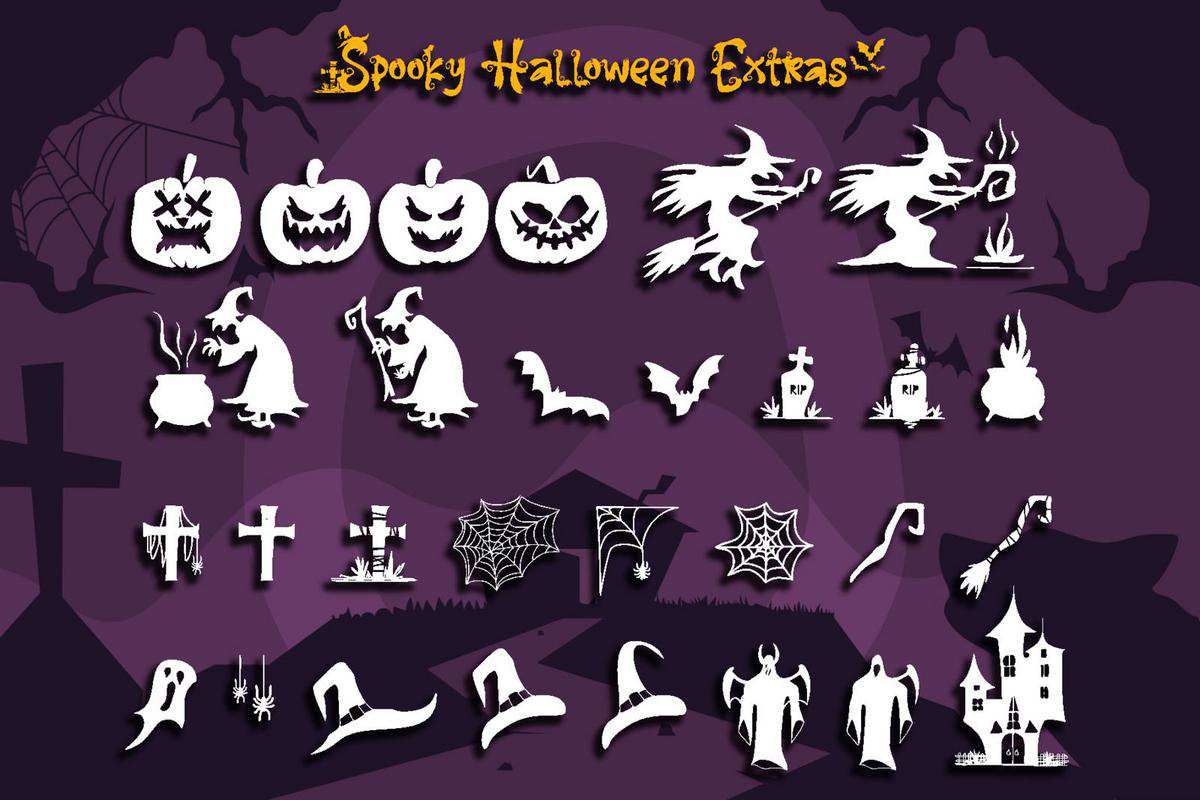
Spooky Halloweenisa ool and scared corative fort.将其用于您的每一个十月设计,并注意其是否持续存在。Spooky Halloweenisp禁止使用,这意味着您可以访问Glyph and Swashease!Spooky Halloweenisa ool and scared corative fort.将其用于您的每一个十月设计,并注意其是否持续存在。Spooky Halloweenisp禁止使用,这意味着您可以访问Glyph and Swashease!